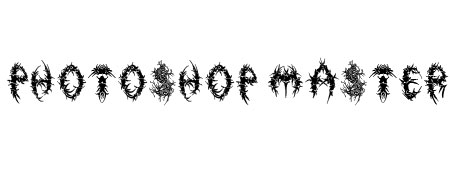
Дополнения Шрифты Татьяна Гапонова 13 августа 2009 Шрифт - FlorAlphabet-Bold Необычный шрифт без поддержки русского языка. Скачать Шрифт - FlorAlphabet-Bold